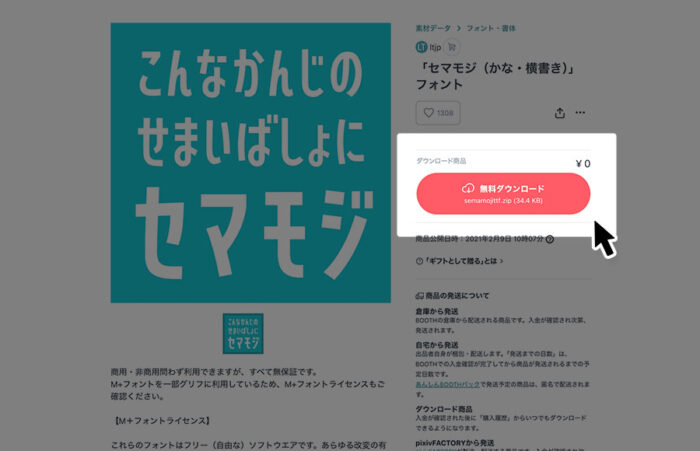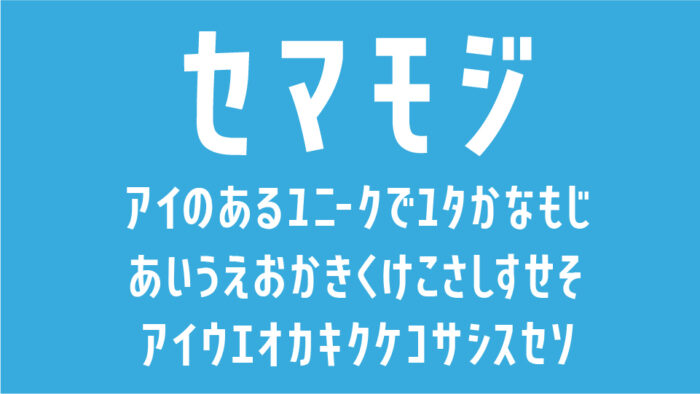
セマモジフォントは、狭い場所にぴったりなフォントとして作られた長体のゴシックフォントです。
限られたスペースにもスマートに収まる、省スペース設計されている細身かな文字フォントとなっています。やや縦長のプロポーションとスッキリした直線的なラインと、どこかリズミカルな雰囲気をもつ可愛らしいフォントです。
収録文字は、ひらがな・カタカナ・アルファベット・数字・記号が収録されています。